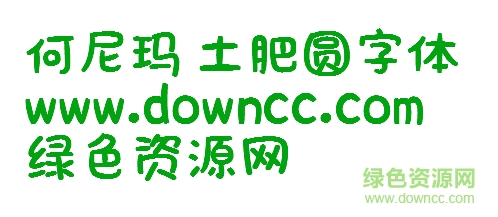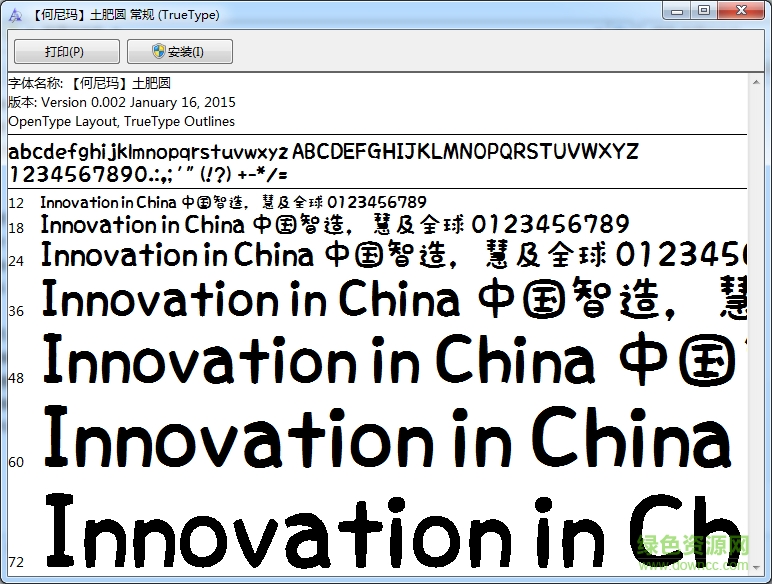
土肥圓字體是何尼瑪創(chuàng)作的海報(bào)字體,也叫作海報(bào)圓圓體,字跡有著圓潤(rùn)的筆觸和大方得體的外觀,給人比較舒適的視覺(jué)呈現(xiàn),綠色資源網(wǎng)誠(chéng)意推薦!
何尼瑪土肥圓體字形呈卡通風(fēng)格,給人一種很可愛(ài)的感覺(jué),大方得體,整體效果十分出眾,廣泛應(yīng)用于平面設(shè)計(jì)、廣告設(shè)計(jì)、報(bào)紙雜志、正文標(biāo)題等領(lǐng)域。
海報(bào)體,是從用刷子隨意書寫的海報(bào)字形象演化而來(lái)。所以也叫隨意體。橫不平,豎不直,結(jié)構(gòu)也不規(guī)范。
其藝術(shù)風(fēng)格:詼諧、隨意、俗野、怪異。